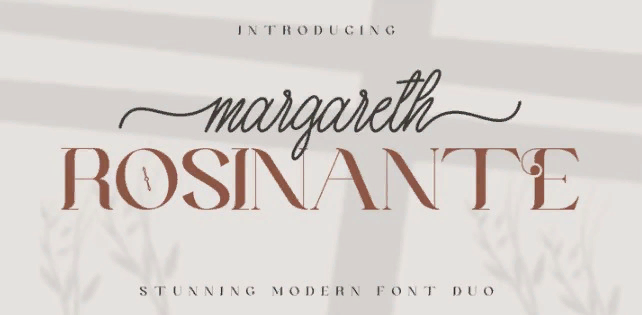
[Myfonts] Margareth Rosinante Font (2021)
Название: Margareth Rosinante Font (2021)
"Margareth Rosinante" - это современное семейство шрифтов с засечками. С роскошью и изысканностью, которые соответствуют друг другу.
Margareth Rosinante создан для эпического сравнения стилей засечек и шрифта.
Резкий контраст между засечками Margaret Rosinante и шрифтом делает это семейство шрифтов всегда уместным в паре с любым дизайном.